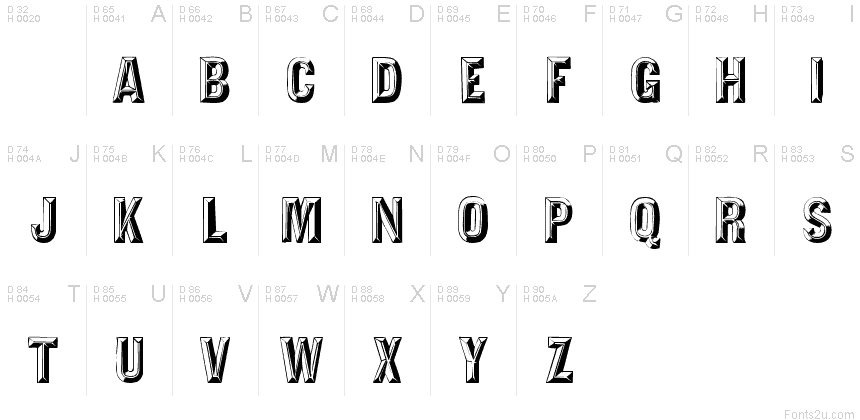
Tejaratchi to darmowy font 3D o wyglądzie ciosanych liter, z ostrymi, ściętymi krawędziami i głębokim, masywnym cieniem. Litery mają architektoniczny, niemal ceremonialny wyraz, a dzięki spiczastym łączeniom i twardym kątom przypominają kamienne rzeźby, a nie luźny, ozdobny krój.
Dzięki temu świetnie sprawdzi się w tytułach plakatów, na okładkach książek, w szkicach logo, ulotkach czy tytułach gier, gdzie odrobina starej, monumentalnej estetyki wzmacnia przekaz. Jako darmowy font, doskonale nadaje się także do krótkich nagłówków, inicjałów i monogramów – fasetowa głębia sprawia, że nawet kilka znaków nabiera wyrazistości i stanowi solidny fundament projektu.